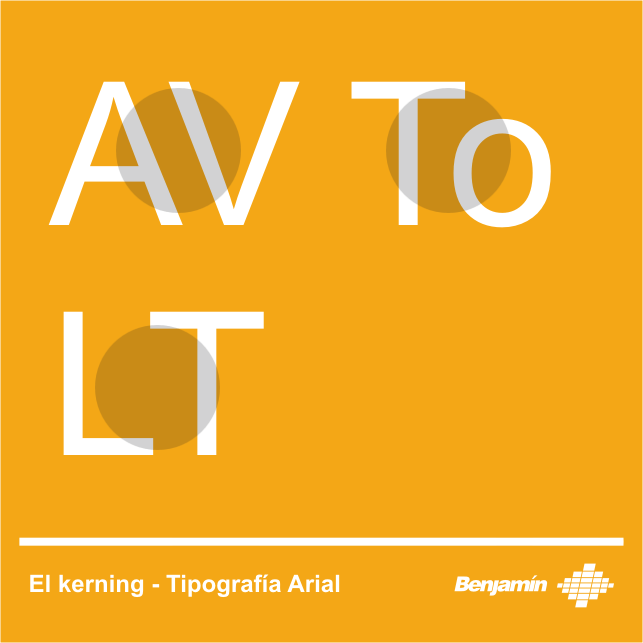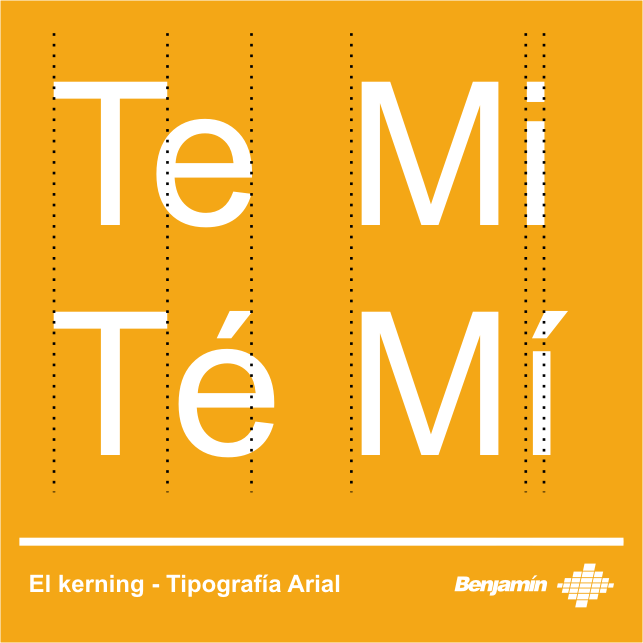
En tipografía, ¿qué es el "kerning"?
El kerming es el espacio existente entre dos pares de letras (y en algunas ocasiones incluso trios) para corregir problemas de ritmo tipográfico. Este problema surgen cuando la forma de dos letras concretas deja un gran espacio entre ellas, como por ejemplo las parejas A-V, T-o, L-T, etc. Para corregir este problema se incluye en el propio archivo de la tipografía una tabla con la relación de espaciado y los pares de letras. Por ejemplo para la pareja AV le daríamos -2, para To sería -3, etcétera.
Un problema que existe con los idiomas distintos al inglés es que la mayoría de las tipografías estan pensada para este idioma, por lo que muchas de ellas no incluyen kerning en las letras con tildes o la ñ. Par comprobarlo podemos hacer la siguiente prueba: escribimos Te y Té y si en el segundo caso existe más separación, sería porque no se pensó en la é con tilde a la hora de hacer los kernings.
En programas como el Illustrator se pueden corregir estos errores.